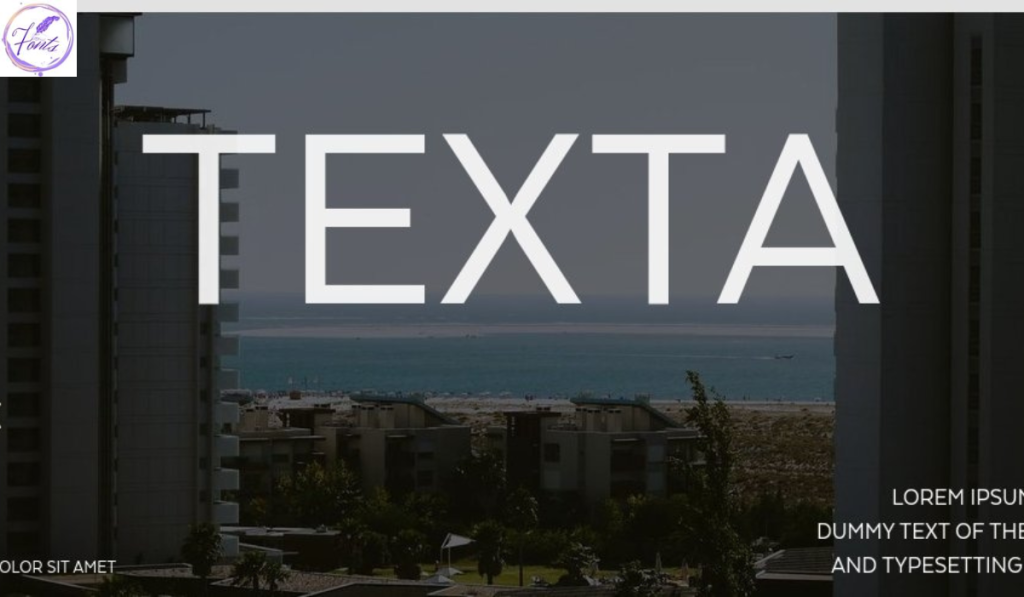
Texta font việt hóa
Tác giả: Daniel Hernández & Miguel Hernández
Ngày phát hành: 2017
Ngôn ngữ: Tiếng Việt, nhiều ngôn ngữ khác
Bộ Font: Texta
Phân loại: Cá tính, độc đáo
Kiểu chữ: Sans-serif (không chân)
Độ dày: Thin, Light, Regular, Medium, Bold, Black, Italic, nhiều độ dày khác nhau
Texta font là một kiểu chữ hiện đại và linh hoạt, được thiết kế bởi Daniel Hernández & Miguel Hernández vào năm 2017. Với những đường nét gọn gàng, dễ đọc và tính ứng dụng cao, texta font mang lại cảm giác chuyên nghiệp và hiện đại cho mọi thiết kế. Font này rất phù hợp cho các dự án từ in ấn, thiết kế web đến các tài liệu quảng cáo và truyền thông. Đặc biệt, texta font đã được Việt hóa hoàn chỉnh, giúp người dùng dễ dàng sử dụng trong các văn bản tiếng Việt mà không gặp bất kỳ trở ngại nào.
Đánh giá texta font
Texta font nhận được nhiều phản hồi tích cực từ cộng đồng thiết kế nhờ vào tính thẩm mỹ và độ dễ đọc cao. Được đánh giá là một trong những font chữ linh hoạt nhất hiện nay, texta font có thể được sử dụng trong nhiều loại dự án khác nhau, từ in ấn đến kỹ thuật số. Khả năng Việt hóa xuất sắc cũng là một điểm cộng lớn, giúp font này trở thành lựa chọn hàng đầu cho các dự án tiếng Việt. Nếu bạn đang tìm kiếm một font chữ vừa hiện đại vừa dễ sử dụng, texta font chắc chắn sẽ là sự lựa chọn hoàn hảo.